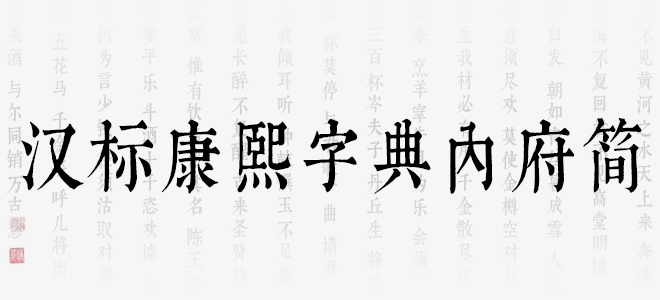
漢標(biāo)康熙字典內(nèi)府簡是以康熙字典為藍(lán)本運(yùn)用軟件制作而成,筆畫流暢飛揚(yáng),結(jié)體左緊右松,開合對比強(qiáng)烈,進(jìn)一步強(qiáng)化了動感。整套字體有如一氣呵成,行筆迅捷華麗,其個性浪漫灑脫,適用于現(xiàn)代詩歌、短文的排版,以及文化、商業(yè)類品牌的廣告語設(shè)計。歡迎喜歡漢標(biāo)康熙字典內(nèi)府簡的朋友前來下載使用。
漢標(biāo)康熙字典內(nèi)府簡